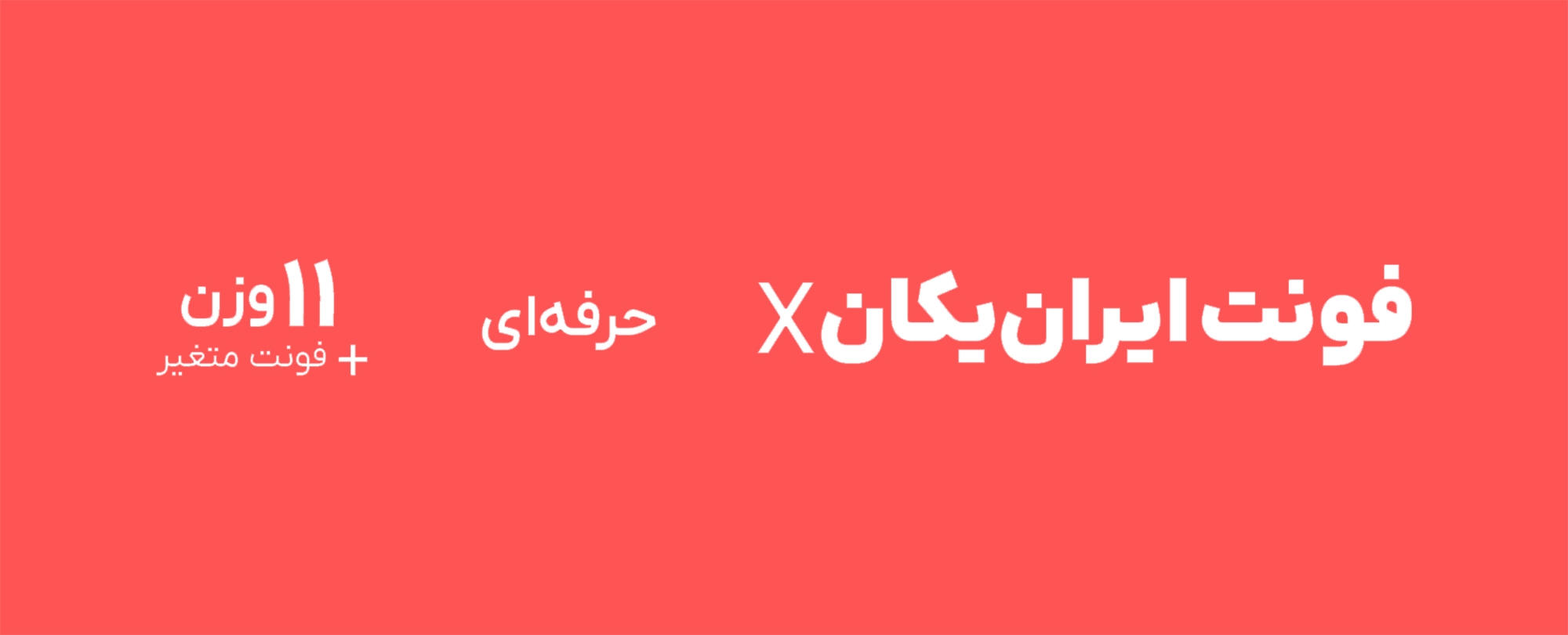
ایرانیکان iranyekan یک فونت سنسِ هندسی است با کمی چاشنی نسخ.
اولین نسخه فونت ایران یکان در سال ۱۳۹۵ منتشر شد. طبق بررسی ما در آن زمان ۲ فونت یکان و ایران سنس بیشترین استفاده را در طراحی رابط کاربری داشت. بنابراین مسلم ابراهیمی تصمیم گرفت تایپی طراحی کند که شخصیتی میان این دو فونت محبوب را داشته باشد.
در فونت ایرانیکان مقداری گردش قلم به ساختار عمودی افقی فونت یکان اضافه شده است و شکل بعضی حروف به ساختار آشنای نسخ نزدیک شده است. نتیجه کار فونتی است دارای هندسه و مدرن اما سیالتر و مانوستر با سلیقه ایرانی. از نظر ما فونت ایرانیکان راحتتر از یکان خوانده میشود و مناسب متن ریز و طولانیتر است. دلیل این ادعا وجود منحنیها و نزدیکتر بودن شکل حروف به ساختار آشنای نسخ است.